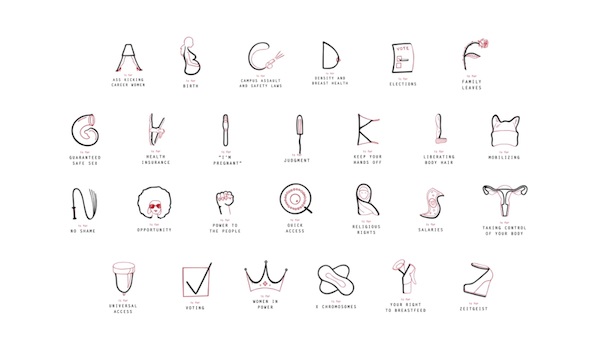
Las feministas ya tienen una fuente tipográfica propia en la lucha por la igualdad de los derechos, de las libertades y por supuesto, del respeto.
de la mano de la agencia neoyorquina Y & R para la empresa Women of Sex Tech se ha desarrollado esta fuente tipográfica denominada “The Feminist Letters“; la cual está pensada para que las personas que simpaticen con la causa puedan expresar sus ideas de una manera activa y más eficiente.
Fuente tipográfica para feministas
Cabe señalar que cada letra de esta fuente esta pensada y diseñada para representar un ámbito en la defensa del feminismo; como el derecho de decidir por su propio cuerpo, la salud y la igualdad entre otros.